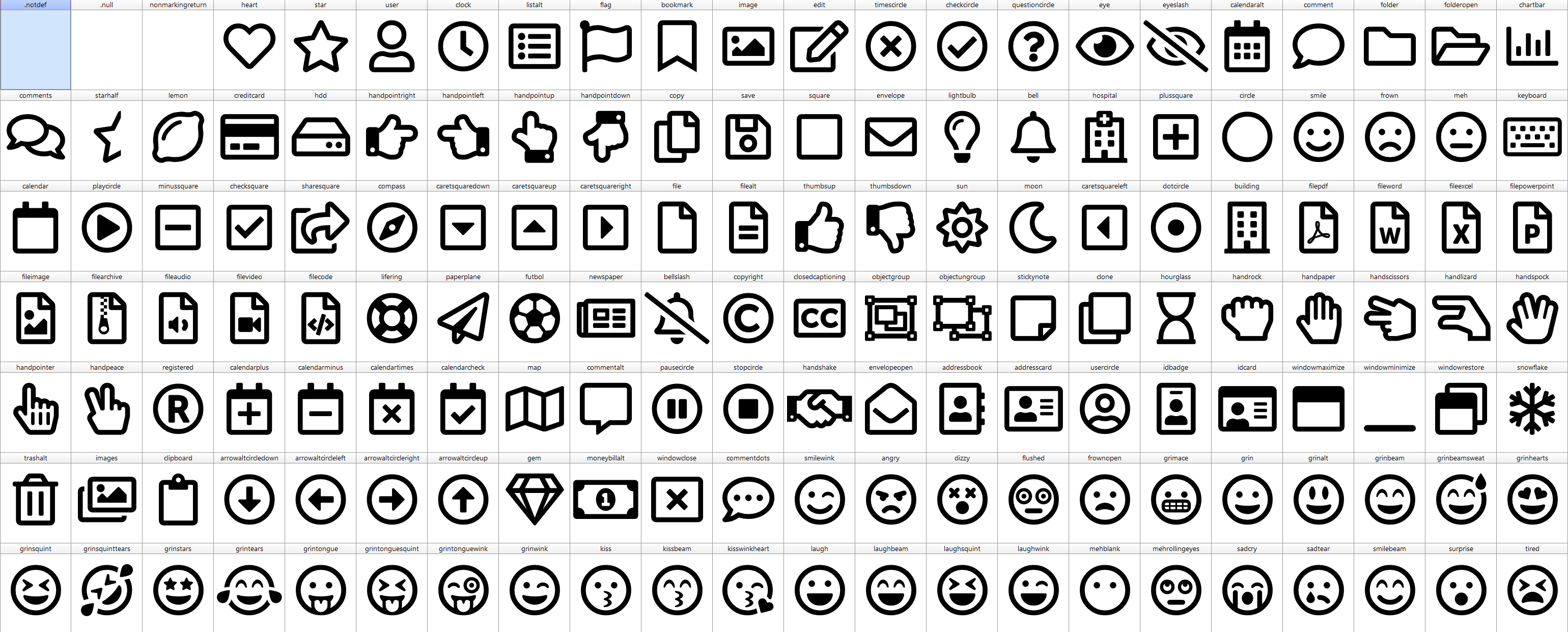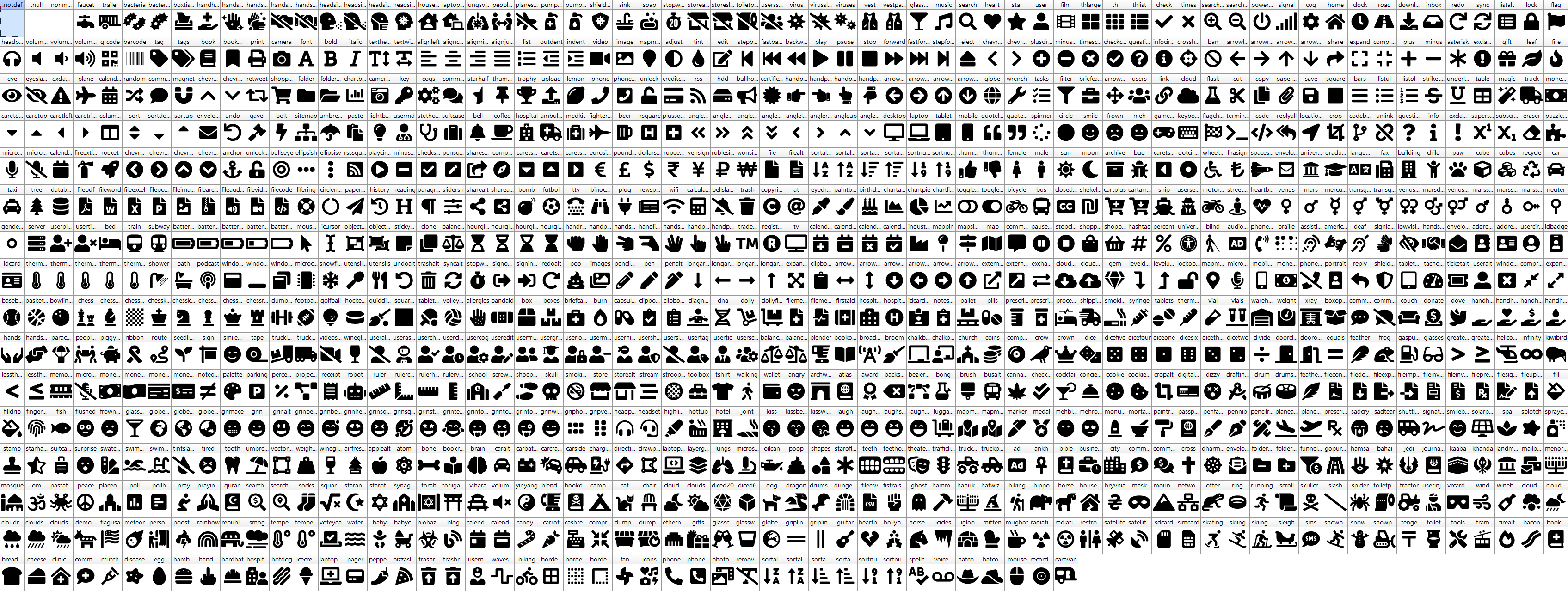
.Net/core - 무료 Icon, Font Awesome 5 사용하기
기존에 glyphicon을 사용하다 일부 단조로움이 있어 찾아보던 중 Font Awesome에서 제공하는 아이콘이 더 다양하여 상황에 맞게 사용할 수 있을 것으로 판단, 이를 적용하면 글을 정리해 본다.
이제 폰트를 사용해보도록 하자. Font Awesome Free 은 총 4가지 로 나누어져 사용할 수 있다.
fas: 기본 아이콘, 가장 다양한 아이콘이 존재한다. fa로도 사용이 가능하다.
far: 배경이 없는 아이콘, 소량 구성되어 있다. 버튼과 같은 배경 색상을 고려해야 할 경우 유용하다.
fab: 브랜드 관련 아이콘, 유명 브랜드와 소프트웨어 아이콘을 사용할 수 있다.
필자가 각 폰트별로 제공되는 아이콘 전체를 캡처해 두었으니 어떤 아이콘이 있는지 간략히 확인해 보면 적용전 도움이 될 것이다.
fab - 브랜드 아이콘, fa-brands-400
far: 배경이 없는 아이콘 fa-regular-400
fas: 기본 아이콘, fa-solid-900